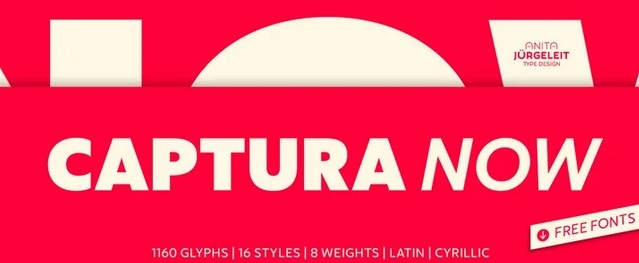
Captura Now
поможет вам создать ваш следующий типографский опыт, отмеченный наградами.
Тщательно отточенные формы и чутко сбалансированные интервалы и кернинг создают мягкий ритм, который придает Captura Now его теплое лицо, совершенное по форме и очертаниям. Расширенная огромным набором символов, Captura Now предлагает свободу преобразования вашего дизайна в мир кириллицы, а также в любой язык на основе латиницы - включая вьетнамский.
Выберите один из предопределенных стилей или постоянно регулируйте вес с помощью новой технологии переменного шрифта*. Многочисленные OpenType-функции, такие как стилистические альтернативы, маленькие прописные буквы, обведенные стрелки, косой ноль и многое другое, были реализованы для упрощения вашего рабочего процесса.